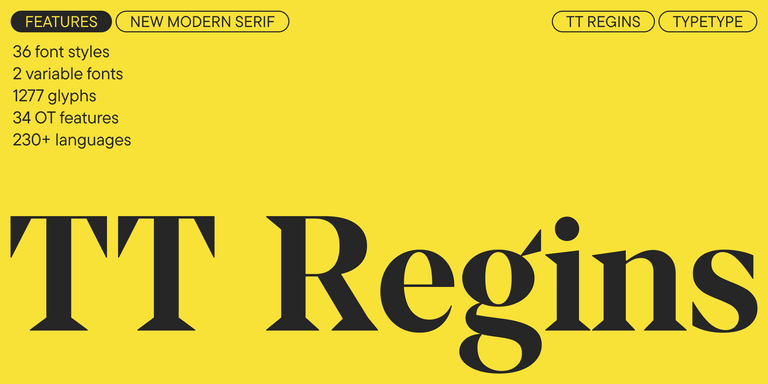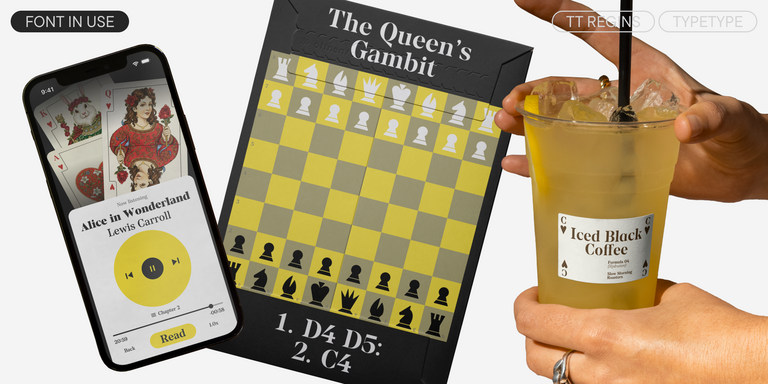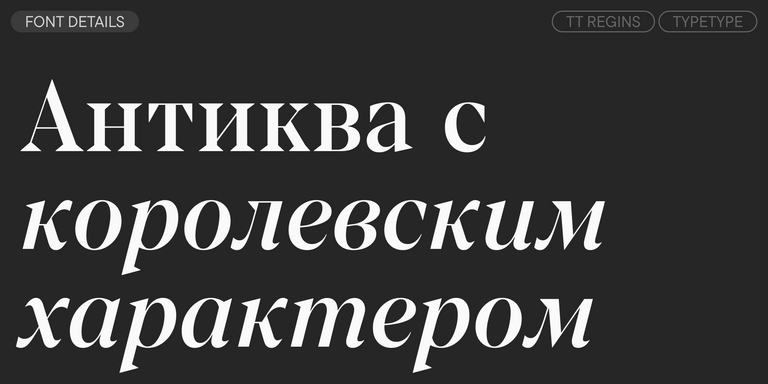
Подборка Монгольских шрифтов
Выберите подходящий шрифт с поддержкой Монгольского языка. Огромная коллекция шрифтовых семейств для любых целей и задач: набор больших текстовых массивов, оформление заголовков для веб-сайтов и печатных изданий, печать на текстиле и других материалах, оформление вывесок и афиш.
Каждый из представленных шрифтов содержит Монгольский алфавит. Широкий выбор символов, знаков валют и пунктуации, шрифтовых начертаний и OpenType фич позволят применять один шрифт для разных проектов. Знаки расширенной латиницы, содержащие диакритические знаки, расширят возможности использования шрифта для разных стран.
Каждый шрифт безупречен с технической точки зрения. Многие шрифты из коллекции содержат вариативное начертание, с помощью которого можно создавать уникальное начертание для проекта.
TT Odellia — старостильная антиква с современным рисунком, вдохновлённая венецианскими шрифтами и классической музыкой.
TT Nooks Serif — акцидентная новостильная антиква с лёгким налётом эгоцентричности. У неё острый и твёрдый, при этом элегантный и статный характер.
TT Chocolates — изящный гуманистический гротеск сo сбалансированными пропорциями, близкими к классическим. Шрифт с приятным дружелюбным характером, который интуитивно воспринимается как что-то знакомое.
TT Nooks Script — шрифт с уникальным рисунком, который не имеет прямых аналогов.
TT Supermolot Neue — технологичный модульный гротеск с футуристическим настроением и мощным функционалом. Яркость его характера сочетается с универсальностью применения.
TT Rationalist — функциональный и оригинальный брусковый шрифт с актуальным рисунком. Он универсален и подходит как для заголовков, так и для массивов текста.
TT Commons™ Classic — универсальный геометрический гротеск для широкого круга задач.
TT Runs — это выразительный шрифт, который идеально впишется в проекты со спортивной тематикой. При этом гарнитура отлично подойдет и для других современных проектов: после обновления сфера ее применения значительно расширилась.
TT Turns — геометрический гротеск с акцентными круглыми знаками и выразительными нависающими элементами. Это универсальный шрифт, который лаконично выглядит и отлично читается в маленьком размере, при этом в крупных кеглях становится акцидентным и проявляет свой характер на максимум. Он энергичный, сильный и динамичный — особенно отчётливо это проявляется в наклонных начертаниях.
TT Regins — шотландская новостильная антиква с королевским характером. Яркий контраст и острые треугольные засечки придают этому шрифту строгий и властный нрав.
TT Quaris — изысканная и современная ленточная антиква. Перед разработкой этой гарнитуры мы провели глубокое исследование архетипов ленточных антикв.
TT Ricordi Allegria — современная ленточная антиква, отличительные особенности которой, гиперболизированная разноширинность в пропорциях, контраст между штрихами, клиновидные окончания штрихов и отсутствие традиционных засечек.
TT Bakers — пластичная антиква с нежным и живым характером. Этот шрифт похож на свежую выпечку: он тёплый и мягкий, особенно в жирных начертаниях.
TT Modernoir — акцидентный гротеск с разноширинными пропорциями. Плавные линии и изящные формы ар-нуво в этом шрифте сочетаются с ритмичностью и импровизационной свободой джаза.
TT Ricordi Greto — неконтрастный флорентийский гротеск с динамичными пропорциями. Это единственный гротеск среди антикв в коллекции TT Ricordi, при этом в нем сохранились едва заметные засечки, отсылающие к прототипу.
TT Firs Neue — скандинавский гротеск, сочетающий выразительные графические элементы с универсальностью использования. Мы проанализировали каждый контур и графический элемент. Пересобрали шрифт заново, чтобы сохранить лучшее и исправить необходимое.
TT Fellows — гуманистический гротеск с механистическими мотивами. Открытые формы, дружелюбно-нейтральный характер тонких весов и ещё более мягкий характер в жирных начертаниях.